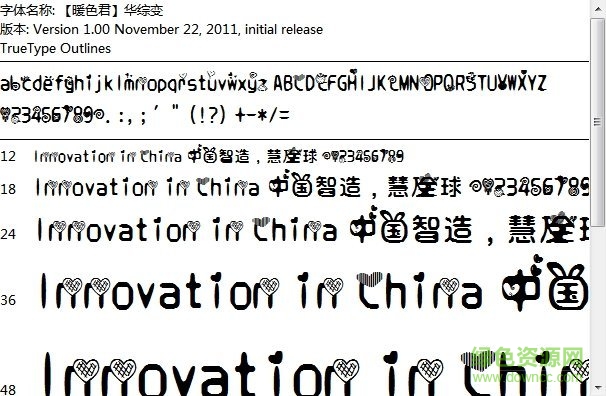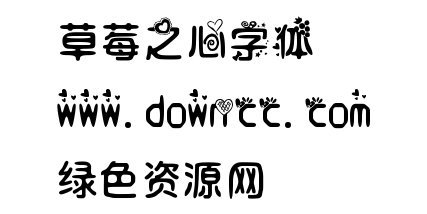
草莓之心字體與草莓戀人字體的風格比較相似,都是偏于卡通q萌的pop字體,字里行間充滿了各種心形圖案,或?qū)嵭摹⒒蚩招牡?,活潑動人,很能吸引讀者的眼光,綠色資源網(wǎng)誠意推薦!
草莓之心字體新浪微博po主暖色君的作品,是在原華康華綜變字體上美化而來,增加了豐富的卡通圖案,心形、草莓性、兔耳朵形狀等,非常有創(chuàng)意。
草莓之心是一款帶心的可愛字體,很能滿足廣大朋友的少女心和童心,給文字增加獨特的裝飾,更加醒目,可以使用在關(guān)于兒童童話、戀愛情侶之間的情意表達,給你的平面設(shè)計增添獨特魅力。